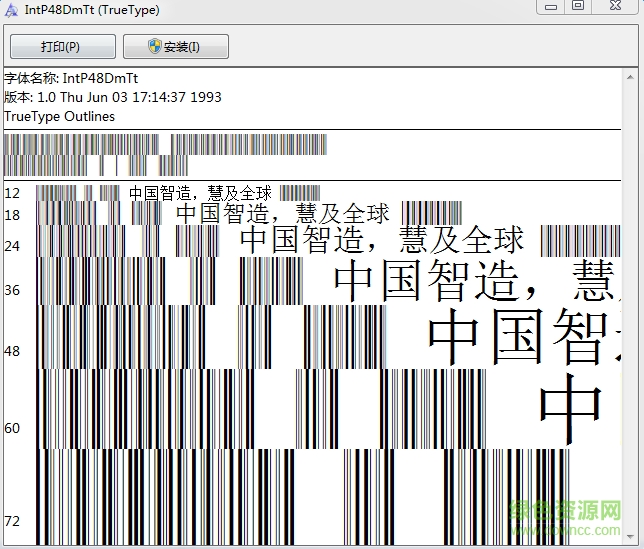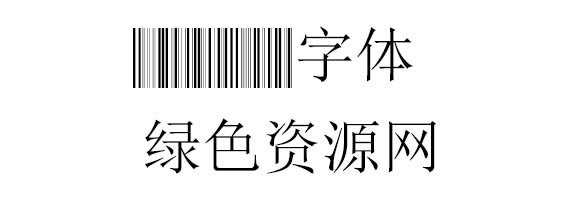
IntP48DmTt
IntP48DmTt字體是一款比較特殊的條形碼電腦字體,這種字體寫出來的字很好看,很有藝術性,具有不同于漢字的字體魅力,可用于多種環(huán)境,歡迎有需要的朋友來綠色資源網下載。
IntP48DmTt字體介紹
IntP48DmTt字體是非常好用的條形碼字體,他給我么展示的文字的另一面